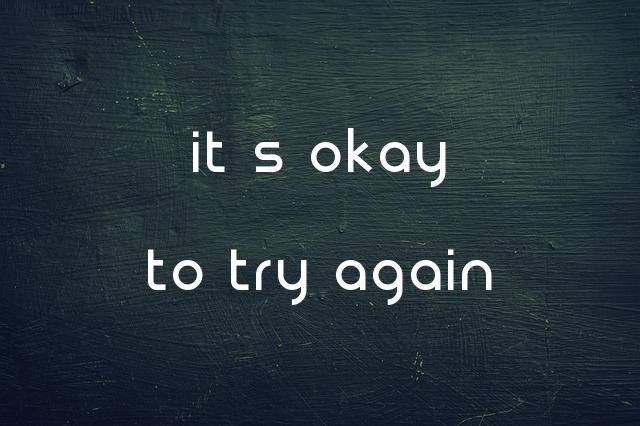
고도마음체는 NHN Commerce가 제작한 귀여운 둥근 손글씨 스타일의 폰트입니다. 아이들의 순수한 감성을 담아 따뜻하고 부드러운 느낌을 전달합니다.
고도마음체은(는)
둥근 스타일, 손글씨, 귀여운 스타일, 레트로, 감성적인, 부드러움, 복실복실 계열의 생김새를 가지고 있으며
초대장, 인사말 카드, 일기/편지 등에서 자주 활용되며, 효과적인 메시지 전달에 적합합니다.
이 폰트는 라이프스타일, 문화/예술, 이벤트/웨딩 분야에 잘 어울리며,
친근한, 감성적인, 편안한 느낌을 담고 있는 것이 특징입니다.